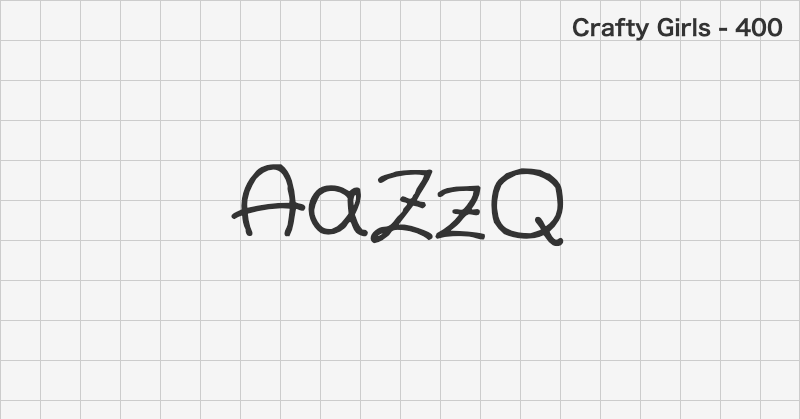
Crafty Girls – 商用利用できる手書きフリーフォント
Crafty Girls は、手描きの要素を取り入れた遊び心あふれるカジュアルな筆記体フォントです。手芸や創作活動にぴったりのデザインが特徴です。
Crafty Girls は、タイプファウンドリー Tart Workshop によって開発され、手芸や創作活動を楽しむためのフォントとして設計されています。クリエイティブなプロジェクトにおいて、個性を引き立てる役割を果たします。